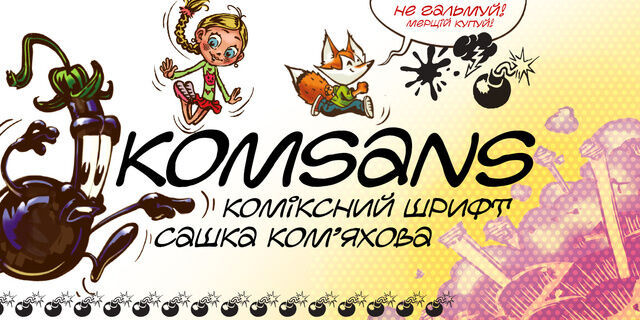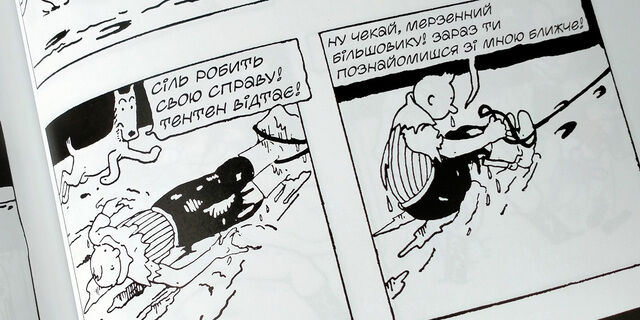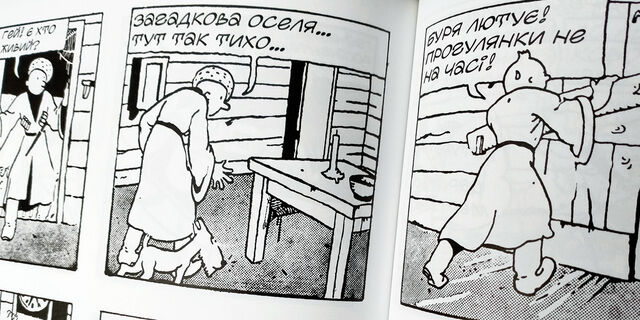
Рукописный юникейс шрифт для рисованных историй в классических комиксных пропорциях на основе почерка автора. Шрифт KomSans имеет веселый игривый характер, хорошо подойдет для приключенческих, юмористических и детских жанров рисованных историй. Шрифт разработал Александр Комьяхов в 2018 году.
лихой, вкусный, оригинальный, свежий, неформальный, смелый, живой, темпераментный, праздничный, творческий, свободный, размашистый, мотивирующий, мягкий, летний, добродушный, дружелюбный, приветливый, добрый, позитивный, милый, симпатичный, природный, натуральный, игривый, шутливый, задорный, веселый, забавный, мультяшный, непоседливый, озорной, детский, счастливый, радостный, проворный, динамичный, быстрый